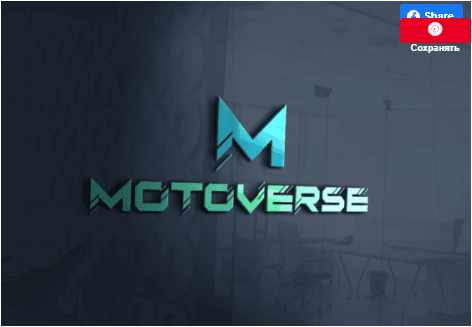
Moto Verse Font
Moto Verse — жирный футуристический дисплейный шрифт с толстыми буквами. Он невероятно хорошо работает с логотипами, брендингом или почти со всем, что требует современной атмосферы.